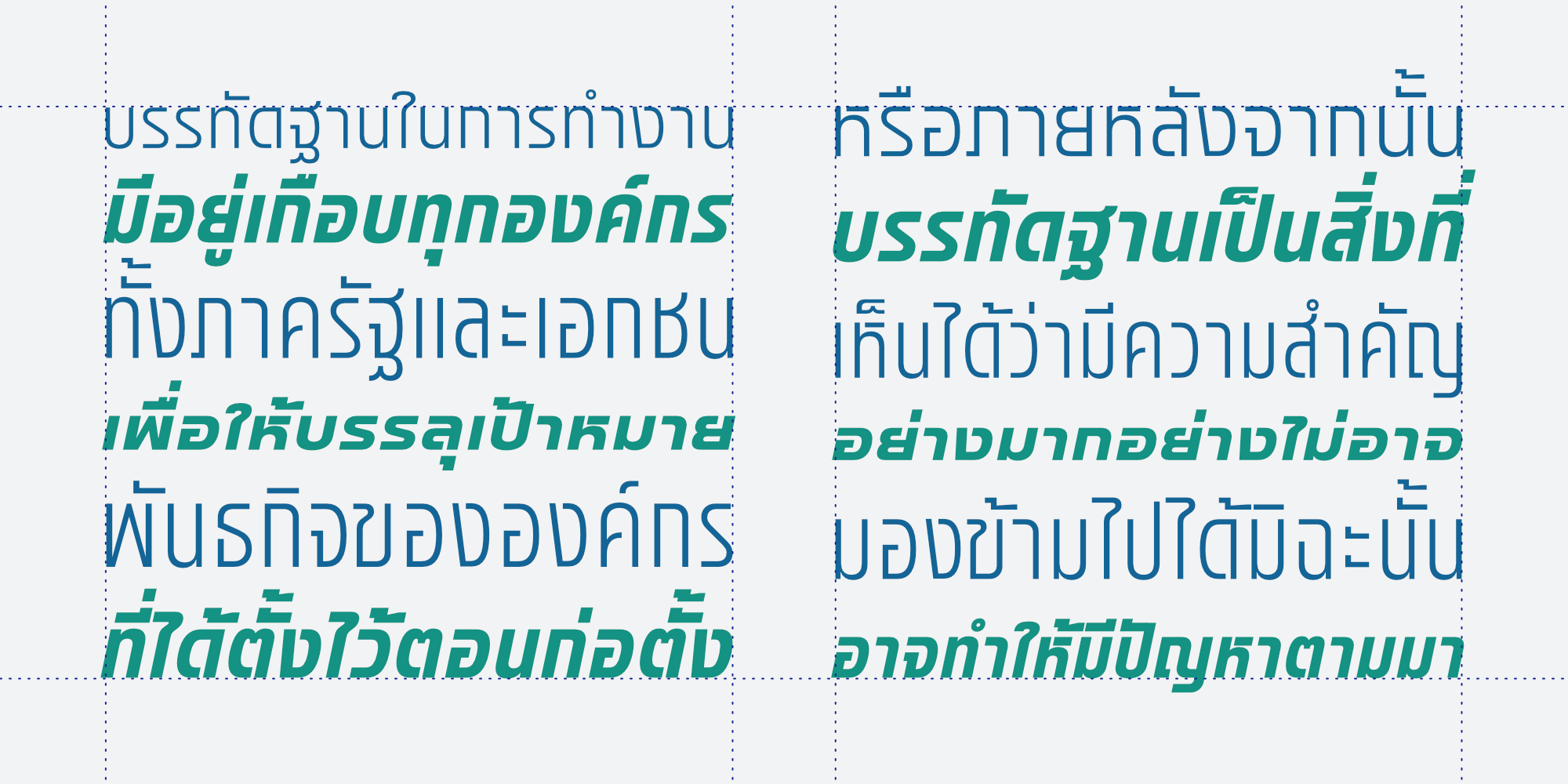
บรรทัด | Bantat
ขื่อฟอนต์ : บรรทัด | Bantat
ฟอนต์ Bantat เป็นแบบอักษร Sans Serif ที่มีความเรียบง่ายโดยออกแบบให้หลังคาและฐานตัวอักษรกลุ่มหนึ่งราบเรียบไปกับเส้นบรรทัด
ผสมกับหลังคาแบบปกติ เพื่อให้มี Dynamic แทนที่จะราบเรียบไปทุกตัวอักษร
ฟอนต์ Bantat มีให้เลือกใช้ 18 น้ำหนัก และ 5 ความกว้าง ทั้งตัวตรงและตัวเอียงรวมแล้วมี 90 Styles และถ้าใช้ฟอนต์แบบ
ฟอนต์ Bantat เหมาะสำหรับงานทั่วไป บนสื่อได้หลากหลายขนาดไม่ว่าจะมีความกว้างหรือแคบ